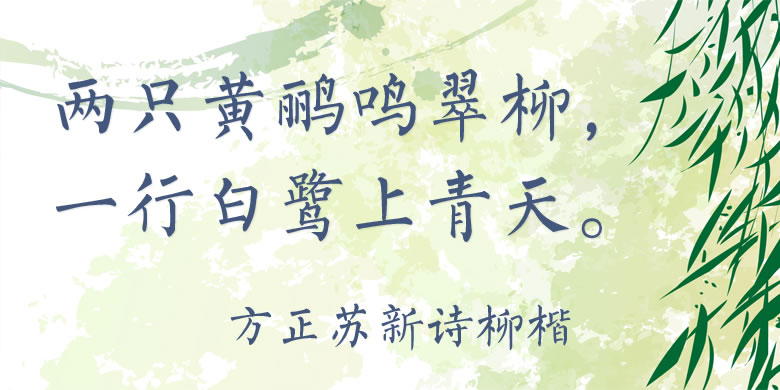
方正苏新诗柳楷
方正苏新诗柳楷,这款字体结构工整、笔画清晰,兼顾美观与易读性,适用于标题、正文、海报、包装、LOGO 等多种场景。字形优雅稳定,风格百搭耐看,适配日常排版与创意设计,让文字呈现更舒适、更具质感。方正苏新诗柳楷一笔一画,皆是细节,以均衡的比例、流畅的线条打造舒适视觉体验,字形端正大气,风格简约现代。无论是商业设计、品牌宣传还是日常排版,都能轻松驾驭,让文字更有格调与力量。方正苏新诗柳楷字体下载。
方正苏新诗柳楷由河南书法家、设计师苏新诗创作。唐代书法家柳公权,在晋人劲媚和颜书雍容雄浑之间,形成了自己的柳体,以骨力劲健见长,后世有“颜筋柳骨”的美誉。方正苏新诗柳楷秉承柳体韵味,笔画遒劲、字形清秀,并兼顾当代字体的设计规则,使其适用于传统文化类的宣传设计。